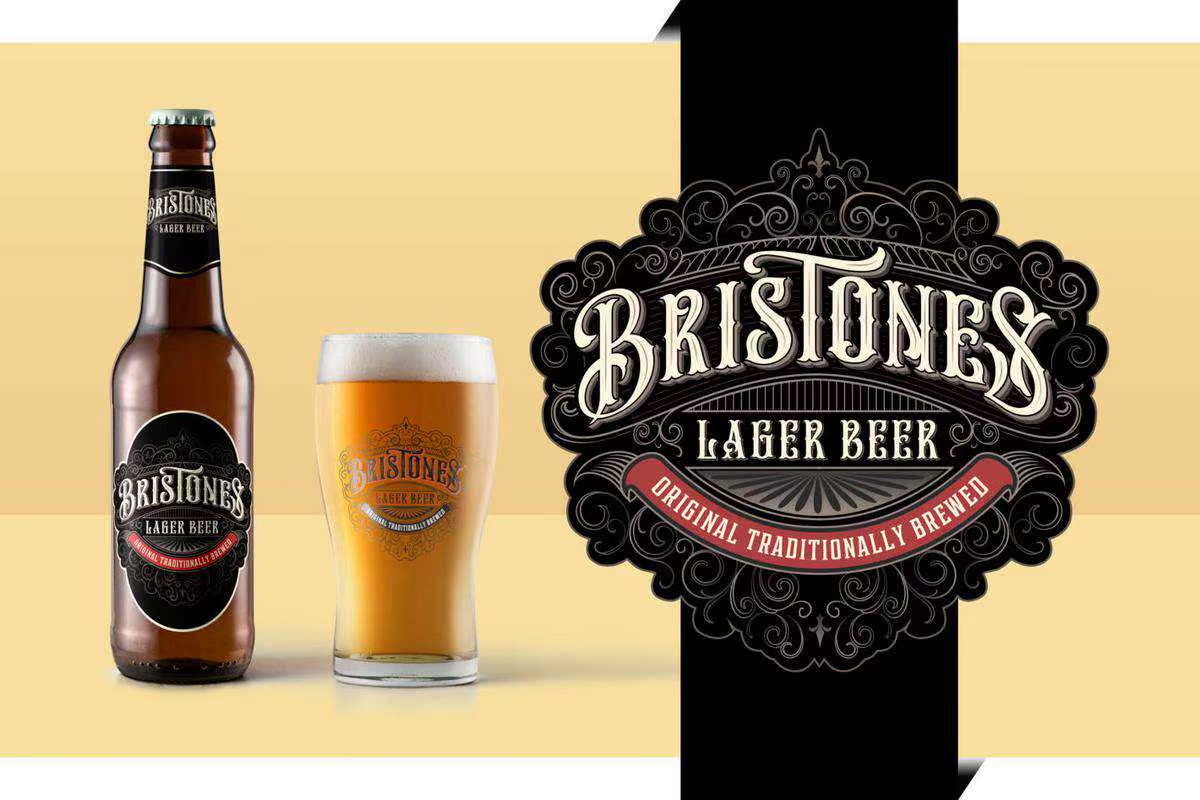
HungryBeast是VictorianthemeFont。另一种旧时尚的感觉是它,因为我们都被认为是那种字体。这种字体将适合于任何你在工作样本的预览中可以看到的显示目的。并且不适用于图层系统,因为无论是哪种类型的字体,它都是维多利亚时代的字体。饥饿感是另一种旧的时尚感觉。因为我们对这种字体都很熟悉。这种字体将适用于您在工作样本的预览中可以看到的任何显示目的。并且不要设置图层系统,因为是谁做的鬼脸?鞋底是这个。